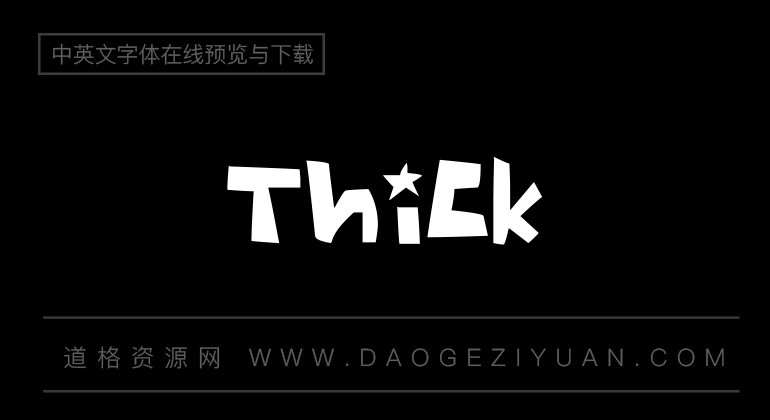
Thick字体是一款粗体字体,由英国设计师James T. Edmondson设计,他的设计理念是在一款经典的粗体字体的基础上增加一些现代感,以获得更加有趣的视觉效果。Thick字体特别适合用于招牌、广告、海报等设计中,也可以用于网页设计、桌面出版和打印应用中。内容介绍
Thick是一款非常不错的手写艺术字体,具有很好的视觉感,适合于文化类的宣传设计、商业类品牌的广告和产品包装设计以及个性化文字排版等较多场景。